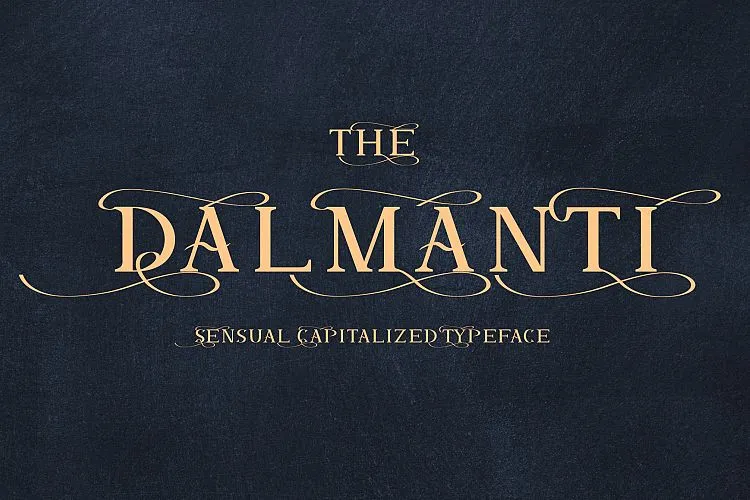
Dalmanti Typeface
A Dalmanti Typeface é uma serifada moderna com toques geométricos e ângulos semi-circulares, oferecendo ao designer uma oportunidade para criar letras elegantes e sedutoras. Inspirado nas personalidades carinhosas dos gêneros alternativos de arte visual, a fonte Dalmanti apresenta um design capilar que abrange uma ampla variedade de aplicações, especialmente adequada para o trabalho em livros, cartões de apresentação, embalagens e até mesmo para posters. Ela oferece ao criador uma ferramenta irresistível para produzir texturas decorativas de alta qualidade, permitindo que cada projeto adquira um toque único e profissional. Dalmanti Font é o tipo certo para aqueles buscando trazer um toque sofisticado à sua arte visual.